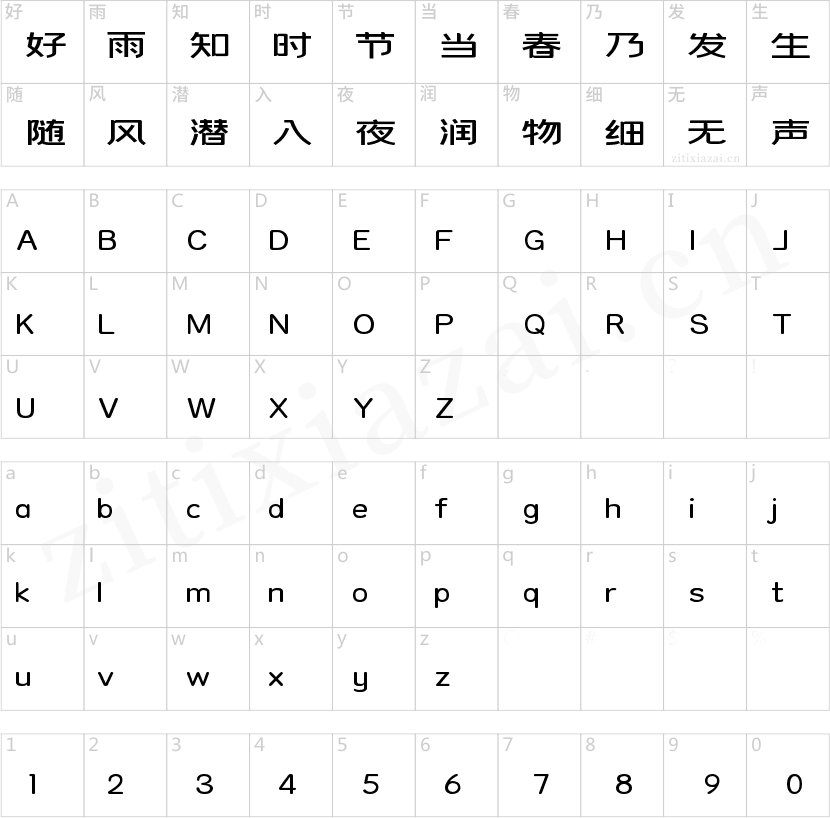
字小魂青森体
字小魂青森体,这款字体结构工整、笔画清晰,兼顾美观与易读性,适用于标题、正文、海报、包装、LOGO 等多种场景。字形优雅稳定,风格百搭耐看,适配日常排版与创意设计,让文字呈现更舒适、更具质感。字小魂青森体一笔一画,皆是细节,以均衡的比例、流畅的线条打造舒适视觉体验,字形端正大气,风格简约现代。无论是商业设计、品牌宣传还是日常排版,都能轻松驾驭,让文字更有格调与力量。字小魂青森体字体下载。
字魂字体字小魂青森体字体是由字魂创意字库设计并生产的一款可商用的字体,被收录于字小魂系列。该字体支持GB-2312标准,包含7106个中文、字母、符号和数字,字体类型偏向基础黑体,具有可爱、简约的风格,在市面上广泛用于广告、正文、化妆美容等场景。